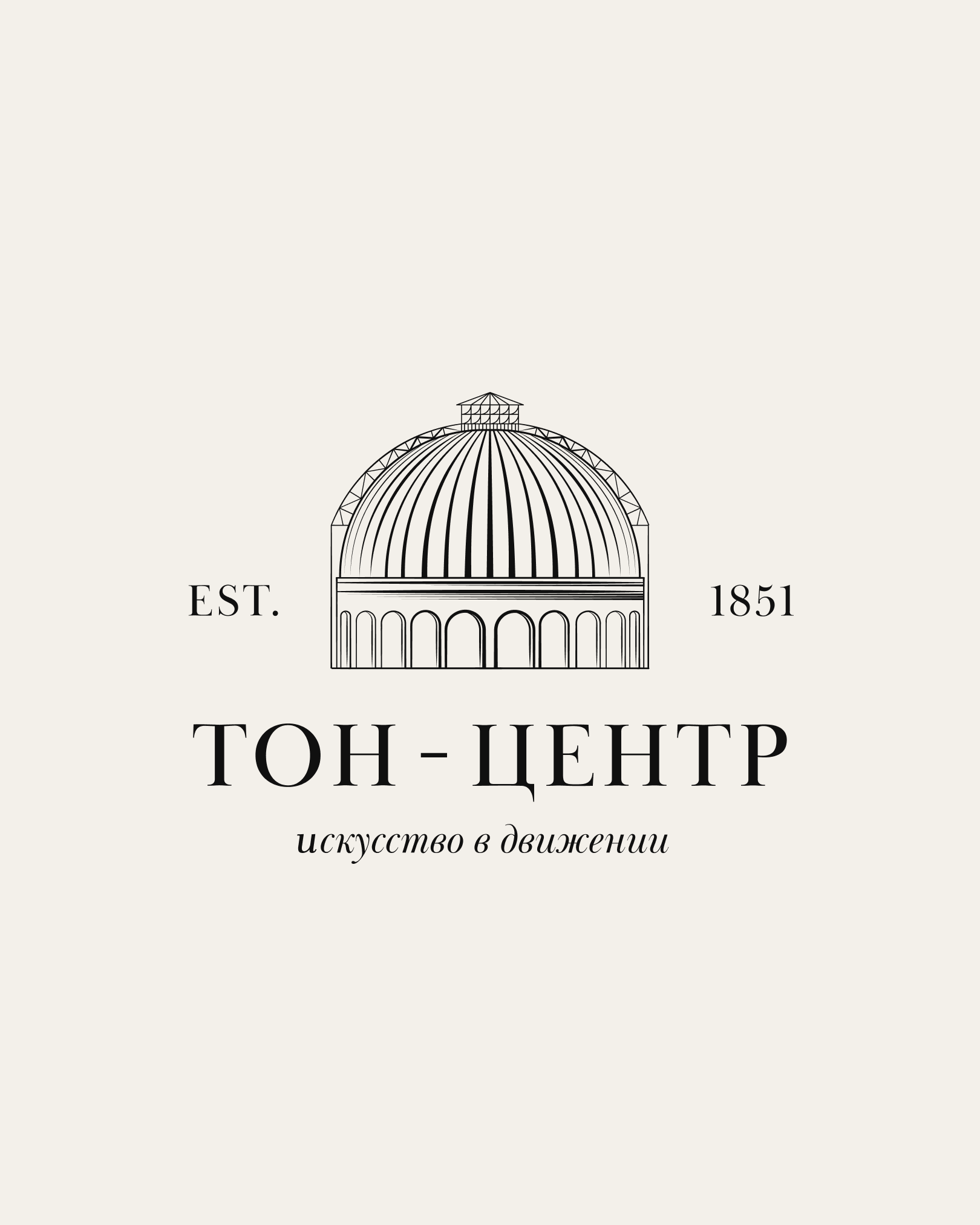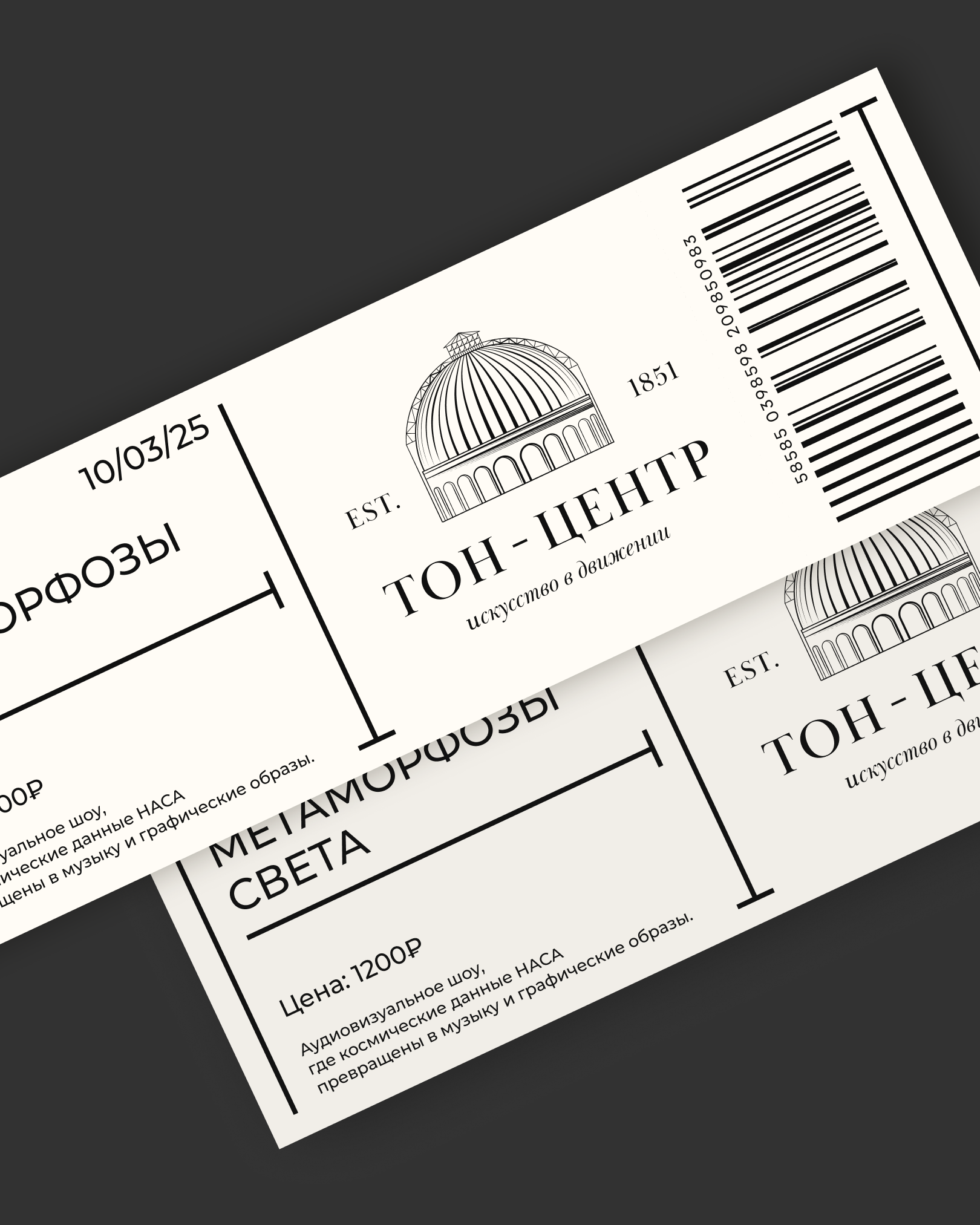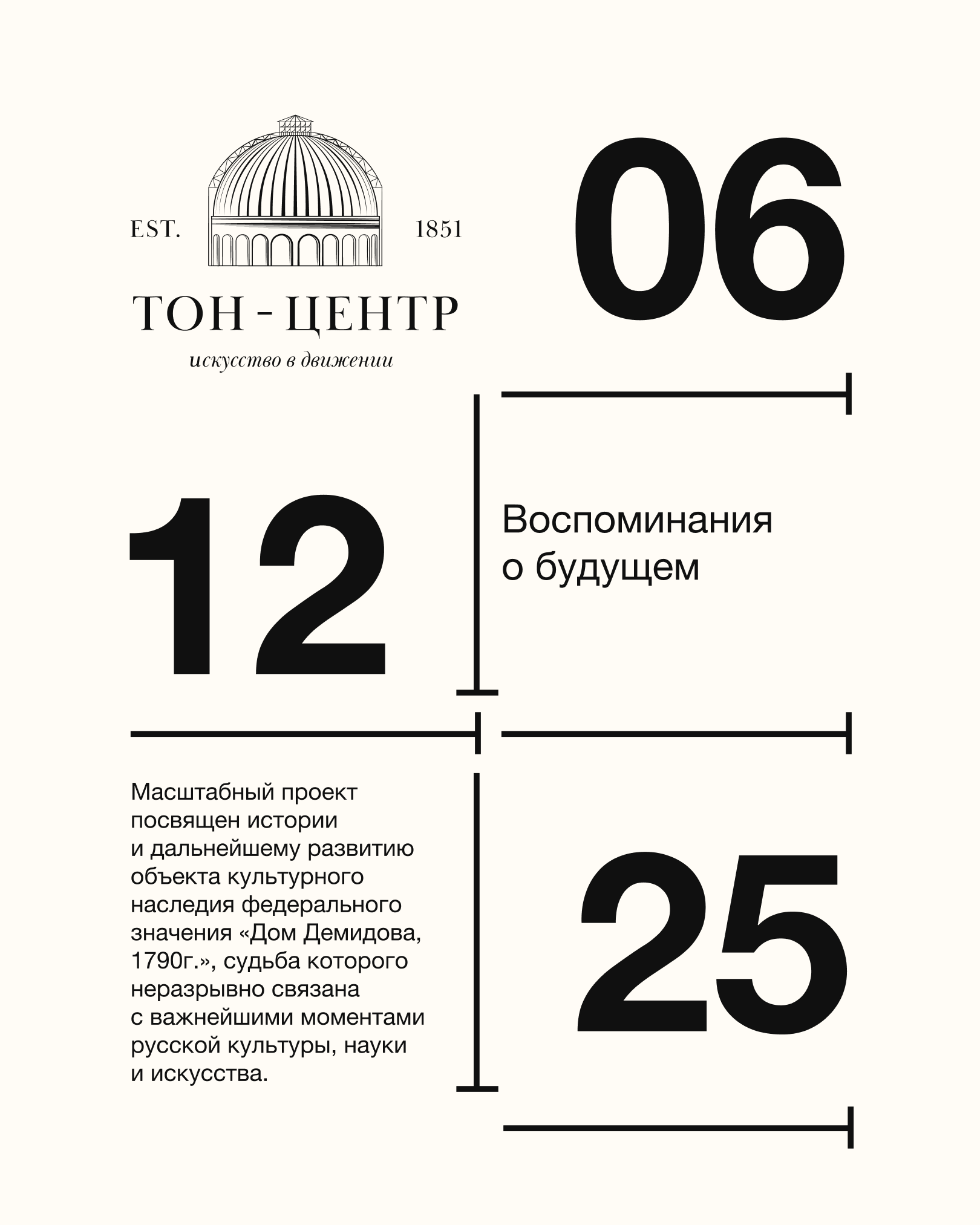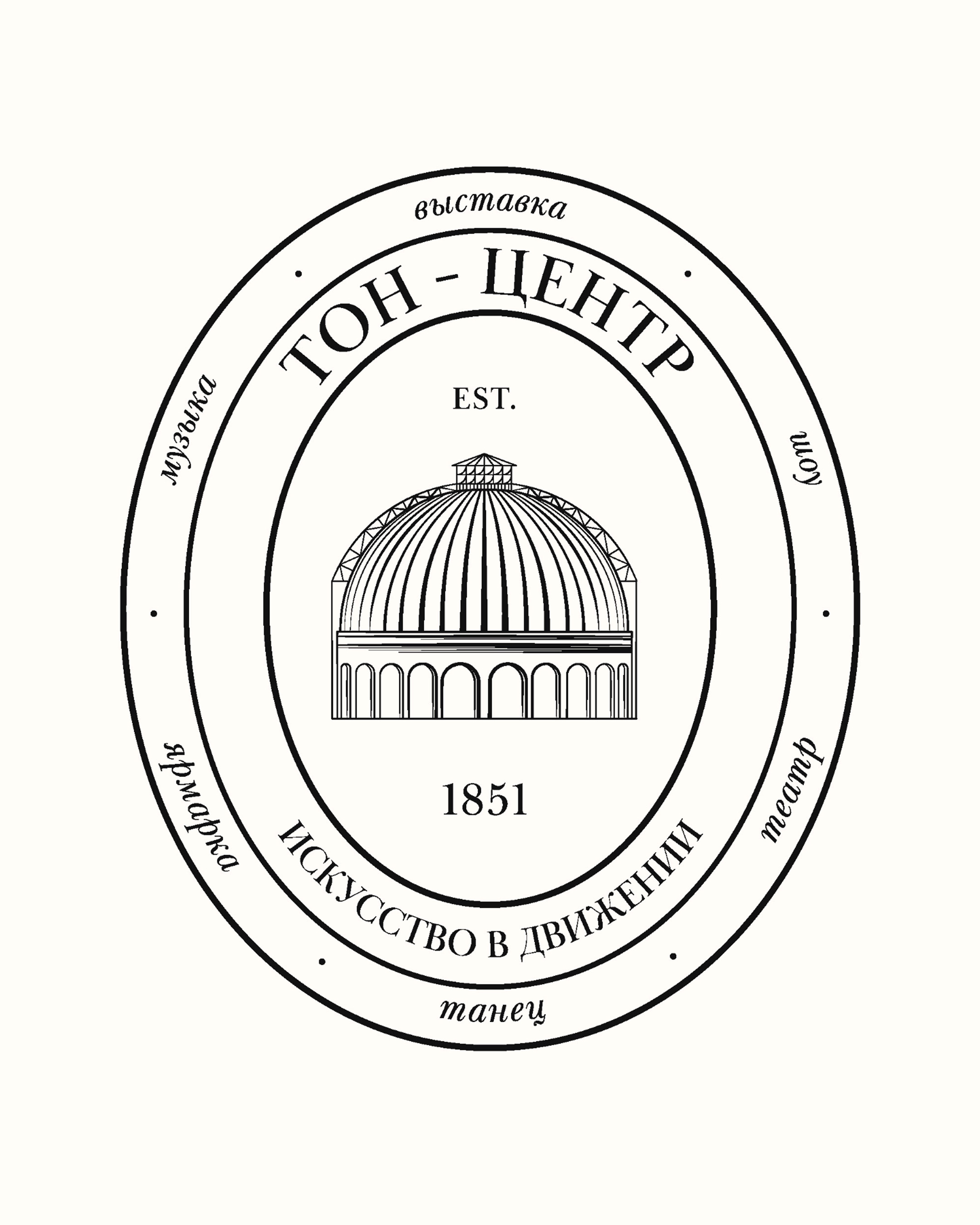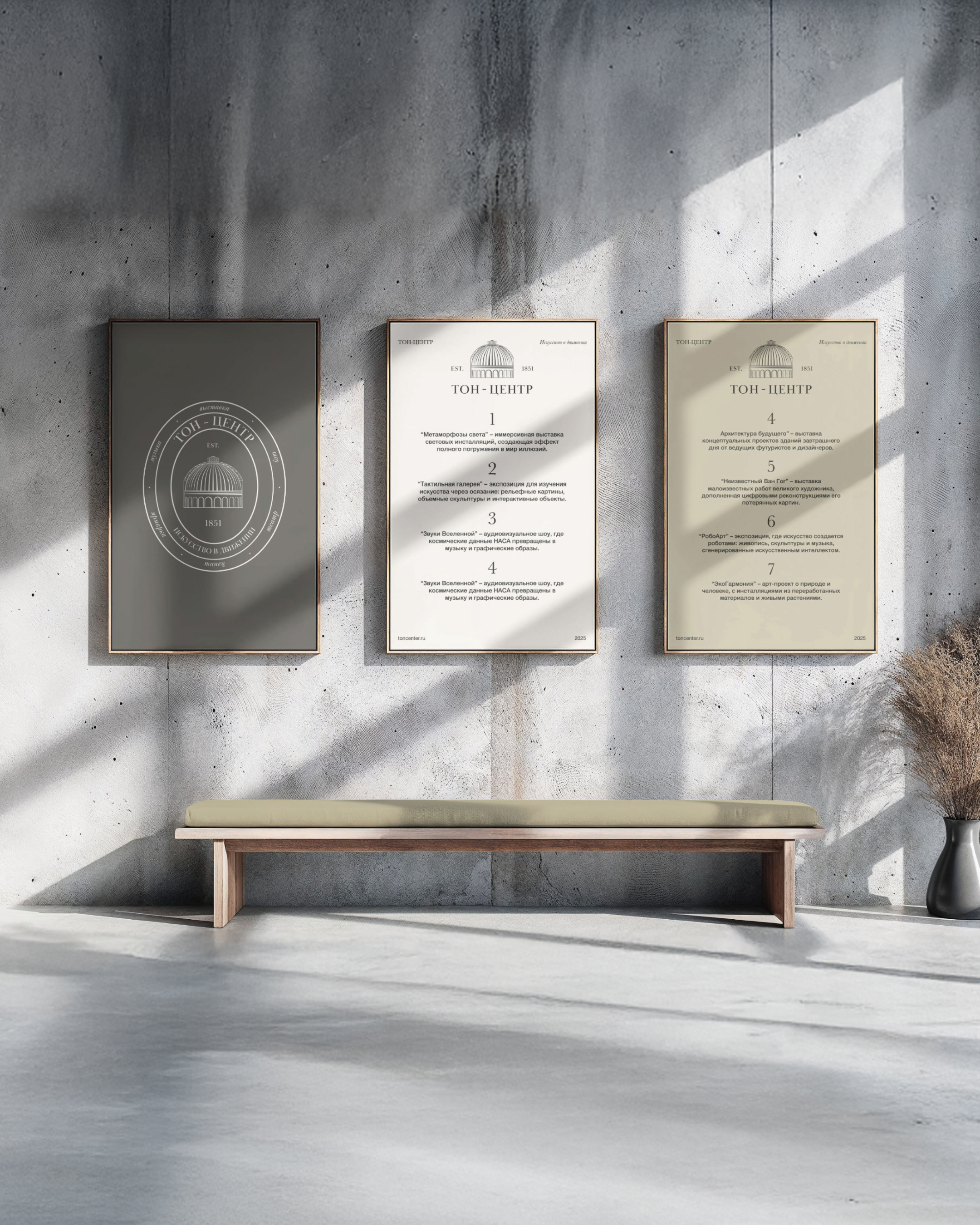
ТОН-ЦЕНТР – мультифункциональное культурное пространство
ТОН-ЦЕНТР – это международная мультифункциональная выставочная площадка, приводящая в движение культурные проекты. Новую жизнь обретает историческое круговое депо, самое первое в России, на площади трёх вокзалов в Москве, спроектированное архитектором Константином Тоном в 1840-х годах.
Сегодня миссия ТОН-ЦЕНТРА – задавать новые траектории актуального искусства и культуры, поддерживая их развитие, так же как круговое депо исторически было создано для движения транспорта и разворачивалo поезда.
10Основой визуального кода культурного пространства ТОН-ЦЕНТР стали подлинные чертежи здания кругового депо XIX века в сечении.
Для основного логотипа мы превратили исторический инженерный рисунок с элементами свода купола и аркадных проёмов в современный графический знак. В основе названия лежит фамилия архитектора депо Константина Тона, а «центр» указывает на точку притяжения разных направлений искусства. Форма эмблемы отсылает к эстетике печаток XIX века, эпохи, когда и было построено круговое депо. Она состоит из трех эллипсов, что также поддерживает цилиндрическую форму строения. Это концентрат смыслов: история здания, миссия культурной институции и спектр направлений искусства зашифрованы в одном знаке.
20Фирменный стиль выставочной площадки ТОН-ЦЕНТР бережно соединяет архитектурное наследие и актуальный дизайн.
Мы выделили особый элемент визуальной айдентики – литера «Т». Этот графический модуль, первая буква в названии, повторяет силуэт одного из локомотивных «стойл» оригинального кругового депо. Т-образные элементы выстраиваются в гибкую сетку, формируют паттерны и акценты.